25招教你设计超赞海报(一)
海报设计充满着无数可能,它不必墨守成规,尽可大胆,创意无限。海报也有着丰富的种类,或是演唱会的大标题型,或是信息量较大的文本型。无论是何种类型,重点都在于在标题、文本、图片及logo间寻得平衡。现在,我们就来和热爱海报设计的小伙伴们分享25招,助同学们做出精彩的海报。
01 颜色的魔力——传递能量,表达情绪,夺人眼球
在设计中,颜色具有无限可能性。它可以传递能量,表达情绪,更可吸引注意力。根据海报的不同主题,可分别选用大胆、柔和或浪漫色系。总之,颜色可以起到至关重要的作用。
在下方的例子中,Savannah音乐节海报选用了柔和的春季色系,以此让大家感受到,这是个户外音乐节,即将欣赏到的音乐类型轻柔美妙,而非重摇滚。
另一种方式则是使用纯色块,只是需要确保各种颜色组合的和谐。这种方式可以令背景十分醒目,下方的例子就很好地诠释了这一点。
亦可对用色数量进行控制,看看下方的活动海报是如何在只使用红黑两色的情况下,用强烈对比度打造出夺人眼球的效果的。
02 尝试不同字体
有时,单单只利用字体,就可以让活动海报传达出丰富的信息。用非衬线粗体表达严肃感,以衬线斜体传递优雅,或选择俏皮的手写体打造趣味性。在选择字体时,至少选择两种——标题用一种,文本则用另一种。
让用字体制造出视觉冲击力吧。快来看看下面两张美丽的活动海报,它们从活动主题“食物”中寻得了灵感~这个例子很好地诠释了如何利用实验性构图成功地向大众传达出活动的核心内容。
如果你也想尝试类似字体形式,确保辅助字体选用简洁型。
下方是一个年度字体设计盛典的海报,它也巧妙地将活动主题与字体结合。
03 划分视觉等级
海报应利于快速阅读,并起到引人注目的作用,划分信息等级就显得尤为重要。如果海报中只有少量文字,那么尽可能选用粗型字体,并结合简洁图形或照片,可参考下方的Columbus Creative的海报。如果海报中含有大量文本,那么就将文字作为焦点,可考虑摆放大标题,并将大量文本视为整个文本块来处理。
04 利用负空间形成巧妙构图
一张图中隐藏着另一张图真的很神奇,当你最终看见被隐藏着的图像时,定能感到有耳目一新。墨尔本餐饮协会海报巧妙地利用餐叉中的负空间,将酒杯结合其中。另有一个利用负空间的方式,将视觉中心聚焦到一个形状较小的物体上,并在周围留出视觉呼吸空间。将文本置于负空间内,以吸引视线,但切勿将其填满。
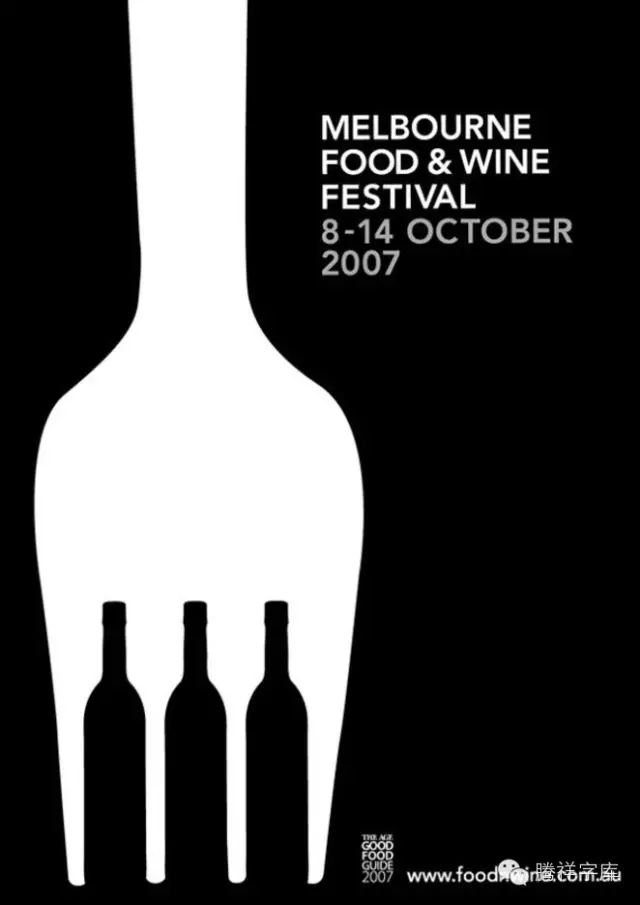
05 删除多余元素,少即是多
有时,少即是多。此法可吸引受众目光,一个简单的词语或一张戏剧性的图片所达到的沟通功效要远远超出大片文本活复杂的图像。不要为了添加而去添加多余的图形或文字。
我们可以注意到这两张海报的共同点,它们都只用一个主导词聚焦受众视线,并以素色营造简洁字型感。
极简主义的优雅在实际应用中仍极具效应。
06 锁定焦点
结合使用或清晰或模糊的图片,可以增强文字所呈现的力量。如果将图片裁切至核心部分,可打造戏剧化效果,吸引视线。下方Chaillot国家戏剧院的海报选用局部唇形图片,而非整脸图片,营造激情和挑逗感。有没有注意到,唇形同时也勾勒出了心形?
07 图形打造视觉亮点
各种形状之间互相连接,而后形成新的形状,它们可以为受众创造出一条视觉线索。我们可以利用各图形来放置文字,或创造出有趣的构图,抑或引导特定的视觉方向。总之,形状在海报设计中极具多样性,并十分实用。
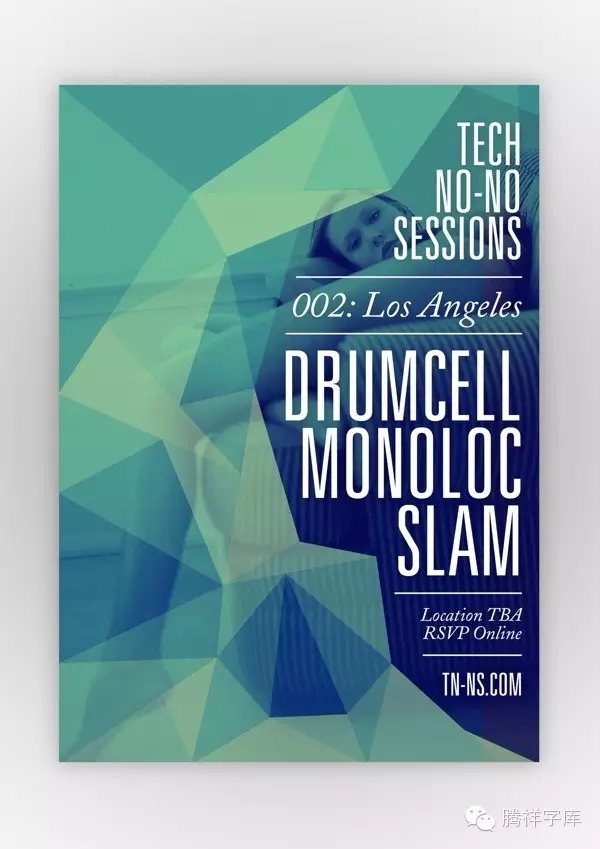
08 构图的种种可能
当所有信息、图片或图形都准备就绪时,便是时候考虑为了便于阅读,如何将其完全打散,再重新组合起来。信息的重新组合过程就像走迷宫,你决定了受众该如何阅读这张海报,如何取得它所表达的信息。多多思考图形和文字间的互相作用。
下方的海报由Calamargraphic 为Malaga盛典设计,文字信息被摆放在海报的右上侧,再利用各个多彩人物图形一齐走向文字信息。
09 层层绘制画面深度
将图形、颜色及文字置于不同层面,打造出深度,用一块小小的画板带领人们进入海报中的小世界。下方的园艺节海报就以分层方式,利用文字和图片互相叠加,创造出园艺人的生活画面。
下方的情人节海报有着异曲同工之妙,它利用了阴影营造出三维立体感。文字的摆放也十分有趣,它们紧靠各个图形,令两者之间互相产生关联。妙哉。